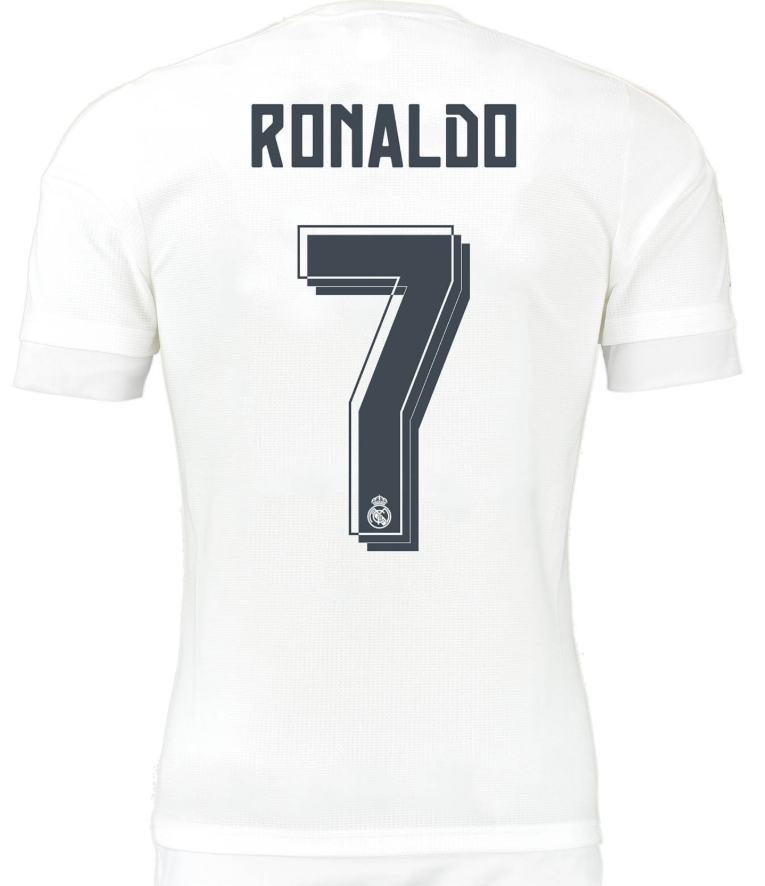
Fonte Real Madrid 2015/2016 (Adidas) – Download TTF da Temporada da Undécima
Para os apaixonados por futebol e design, poucas temporadas são tão emblemáticas quanto a de 2015/2016. Foi o ano em que o Real Madrid, sob o comando de Zinedine Zidane, conquistou a histórica “La Undécima” (11ª taça da Champions League).
Neste post, trazemos para você a tipografia oficial utilizada pela Adidas nos uniformes dessa jornada vitoriosa. Se você quer recriar a camisa usada por lendas como Cristiano Ronaldo, Sergio Ramos e Gareth Bale, este é o arquivo essencial para o seu projeto.
Estilo Visual e Aplicação
A fonte desenvolvida pela Adidas para a temporada 15/16 do Real Madrid foge do minimalismo excessivo. Ela apresenta um design “blocky” (em blocos), com ângulos levemente arredondados nas bordas internas, mas mantendo uma estrutura externa retangular e robusta.
Visualmente, ela transmite força e estabilidade. Um detalhe interessante é a aplicação de um efeito de camadas (ou inline) nos números quando usados na versão de copas (Champions League), diferenciando-se da tipografia padrão da La Liga. Esta fonte combina perfeitamente com o branco clássico do uniforme titular e com o cinza “Silver Glory” do uniforme reserva daquela época.
Dica de Design: Para um realismo perfeito, ao aplicar o nome dos jogadores, use um espaçamento ligeiramente condensado. Nos números, a versão vetorial permite aplicar a textura de “três listras” característica da marca alemã, caso seu projeto exija o detalhe minucioso.